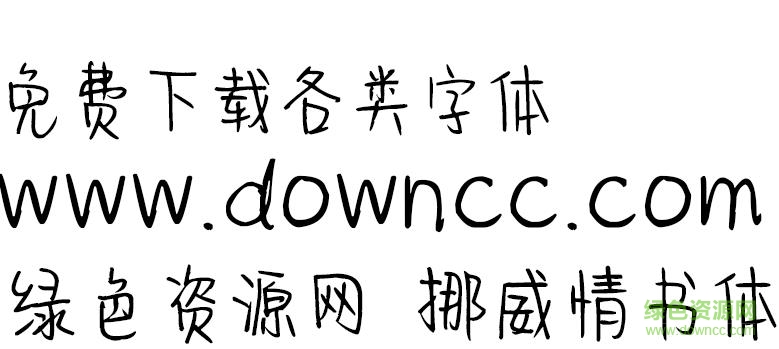
挪威情書體字體擁有十分經(jīng)典的字體樣式,每一個(gè)字都擁有自己的獨(dú)特性格,讓你觀看到字體的時(shí)候能夠感受到舒適的體驗(yàn),擁有精美的字體風(fēng)格,更有讓你在使用的時(shí)候
這款字體真的能夠帶給你獨(dú)特的情書體驗(yàn),是用戶們?cè)跁鴮懬闀臅r(shí)候最適合的字體,給你的另一半怦然心動(dòng)的體驗(yàn)哦!